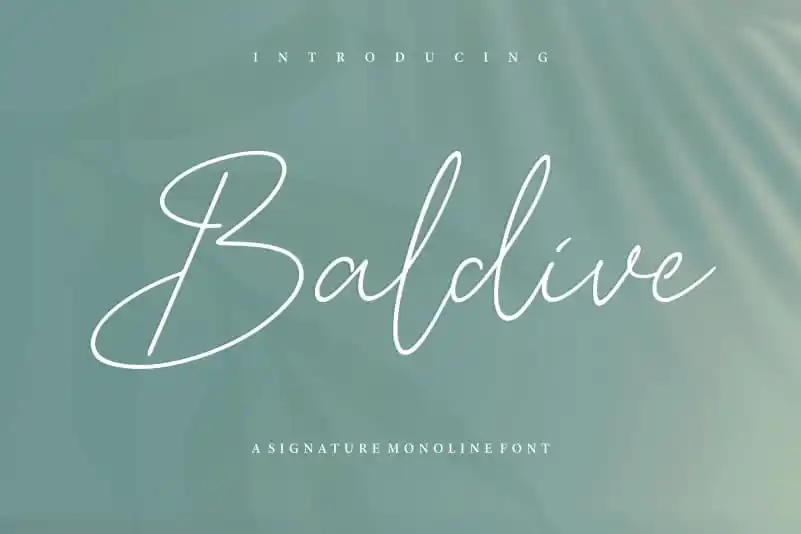
Baldive Signature Monoline Font – Download Grátis
A Baldive Signature Monoline Font é uma escolha ideal para os amantes de gráficos contemporâneos. Esta elegante fonte pode ser utilizada em diversos formatos, desde a identidade visual de um produto até a capa de uma revista ou o design de uma marca. Suas linhas finas e bem definidas se destacam como uma opção perfeita para expressar texturas e estilos inovadores em qualquer aplicação digital, desde postagens nas redes sociais aos desígnios de casamentos. Seja você um criador de conteúdo ou designer gráfico, a Baldive Signature Monoline font proporciona flexibilidade quando se trata de expressar sua mensagem através do design. Suas linhas monolíneas permitem que o texto fique claro e destacado, seja em alta definição ou aplicado sobre backgrounds mais vibrantes. Esta elegante fonte é a perfeita escolha para os projetos que exigem uma identidade visual moderna e sofisticada. Ela se destaca como a solução ideal para aqueles buscando um estilo inovador, com sua proposta versátil capaz de atender ao máximo da variedade de necessidades do design gráfico atual.